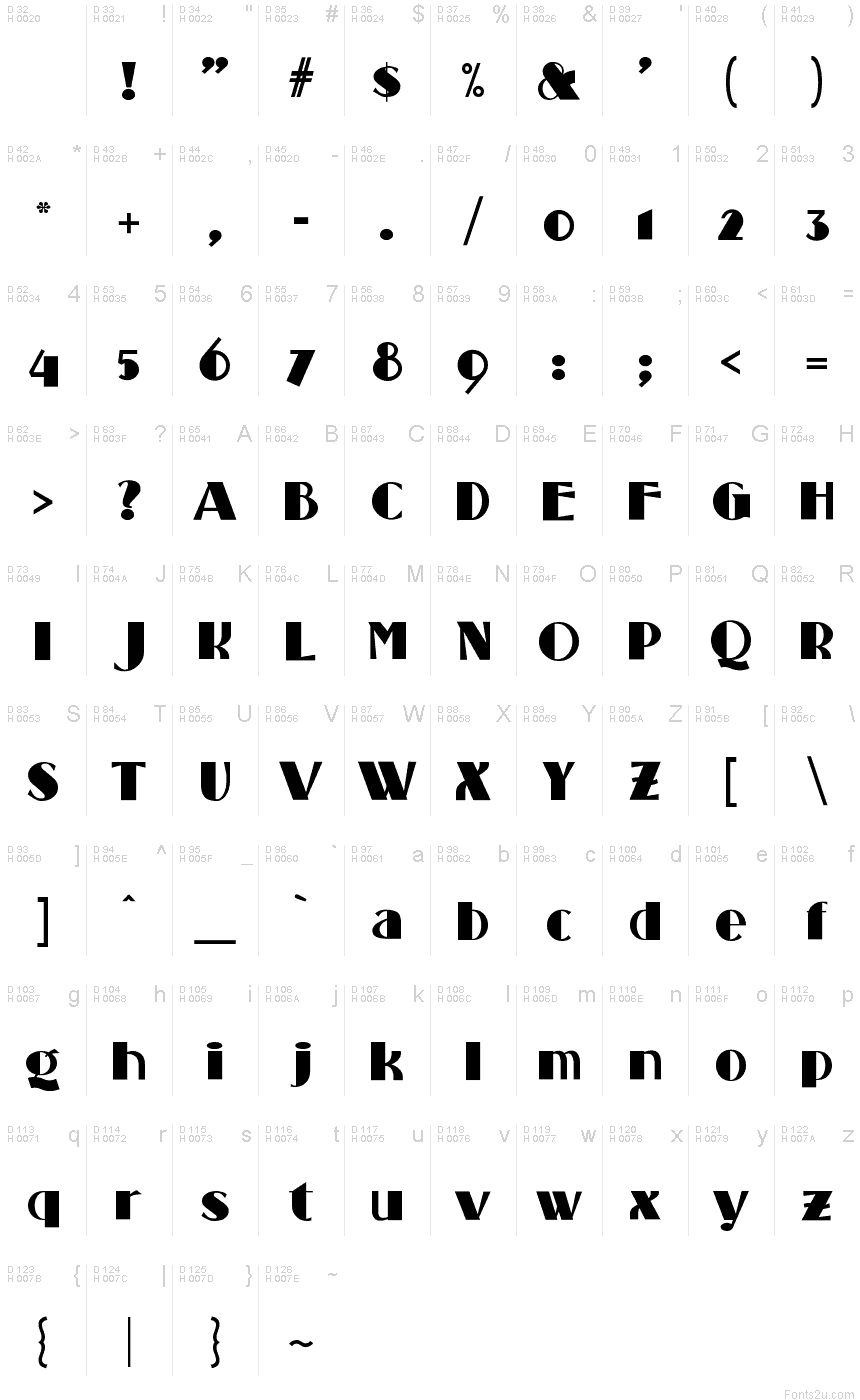
Standing Room Only, bezplatné retro písmo typu display od Nicka Curtise, evokuje atmosféru starých divadelních plakátů s výrazným kontrastem a mírně dramatickým nádechem. Písmena kombinují ladné křivky s ostrými hranami, jako by byla vystřižená z papíru, takže písmo působí elegantně a zároveň stísněně, jako titulky namačkané na divadelní tabuli.
Díky tomu je toto bezplatné písmo přirozenou volbou pro plakátové titulky, názvy na obálkách časopisů, branding kabaretů či lounge barů, obaly alb a úvodní titulky, kde se hodí trocha divadelní atmosféry. Nejlépe funguje v krátkých sazbách, zejména u jmen a úderných nadpisů, protože vysoké, vysoce kontrastní tvary a ostré spoje vytvářejí velmi rychle silný rytmus.